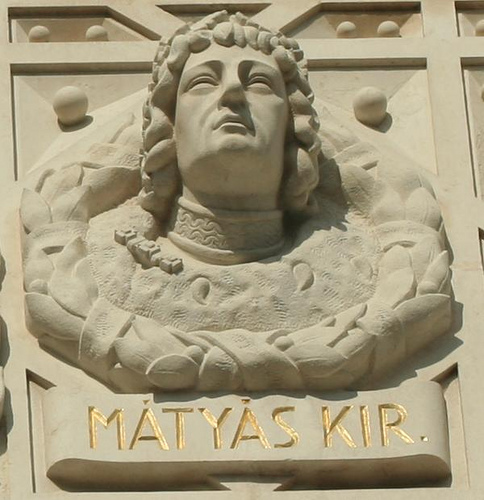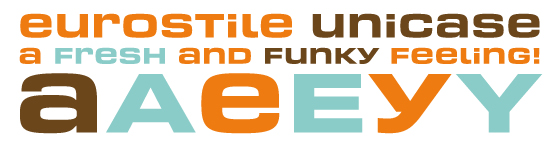
Unicase-Schrift mit Umlauten
ich versuche gerade, eine relativ breit laufende und eher fette unicaseschrift zu entwerfen, und komme mit den Umlauten nicht weiter. Zum Vergleich: etwa so wie die (eurostile unicase)
Ich störe mich total daran, dass die ä-/ö-/ü-Pünktchen die einzigen Elemente sind, die dann aus der so geradlinigen und sauberen gleichen Höhe herausragen.
Was meint ihr, wäre es um der Gleichmäßigkeit Willen in Ordnung, wenn ich statt ä ein æ, statt ö ein œ und statt ü irgendwas ähnliches – ein zusammengezogenes ue – einbaue, oder bricht das die orthografischen Regeln zu sehr und irritiert nur?
Wart mal aufs TypoJournal 4 (kommt in 3 Wochen oder so). Da hat Florian Hardwig in einem Artikel alle Methoden, die Umlaute einzubauen und einzuziehen klassifiziert und mit Beispielfotos versehen. Da kannst du dir einen perfekten Überblick verschaffen. :-)
wenn ich statt ä ein æ, statt ö ein œ
Mhh, nee.
Besser wären OpenType-Varianten. Mal eingezogen, mal nicht.
ich weiss nicht was du mit der schrift vor hast aber es gibt mehr zeichen als ä, ö, ü es gibt auch é, á, ǎ, ñ u. s. w. die lassen sich schwer anders darstellen.
Ja, dass es mehr Umlaut- und Akzentzeichen gibt, weiß ich auch ;) Aber für die geplante Anwendung werden nur äöü gebraucht.
Leider muss die Schrift noch diese Woche fertig (bzw. benutzbar :baeh: ) werden. Ja, dann werd ich es wohl mit verschiedenen OpenType-Varianten versuchen.
Aber ich bin dennoch sehr gespannt auf den Artikel bzw. auf das ganze Journal! :-P
Und wie wäre es, wenn man es ähnlich wie in deinem Beispiel mit der Eurostyle Unicase mit dem kleinen i macht, hier ist ja auch der Punkt in das Rechteck hinein gezogen, und dafür eben der Buchstabe in der Höhe verringert. Beim Ä lassen sich die Umlaut-Punlte ja auch rechts und links neben den eher dreieckigen Buchstaben setzen, beim Ü würde ich die senkrechten Stämme des U einfach teilen, undf beim Ö das O verflachen, und die Umlaut-Punkte eher breit machen, um so wieder das gefüllte Rechteck zu erzeugen.
So ähnlich hatte ich das schon ausprobiert, sah aber wegen der breiten Buchstaben sehr unausgeglichen aus und die Umlautbuchstaben wirkten wie Fremdkörper, die viel mehr ins Auge gefallen sind, als mit Überlängen. Deshalb hab ich es erstmal bei Überlängen belassen…
Grinsekatze, du könntest auch mit Aussparung arbeiten. Hier eine schnelle Skizze:
Das geht natürlich viel, viel schöner, als ich es hier gemacht habe.
Ich musste spontan an das 800-Jahre-Dessau-Logo denken. ;-)
Bei deinem Beispiel habe ich das Problem, dass es sich potenziell um ein Ö und Ü handeln könnte. Wie wäre es stattdessen damit, die Punkte in die Binnenräume/Punzen der Buchstaben zu verbannen? Die Ö-Punkte in die Punze des Ös usw.
Darüber hinaus findest du in der Flickr-Gruppe Fancy Diacritics reichlich Inspiration für Möglichkeiten der Umlautpositionierung.
Z.B. in der Super Grotesk? [PDF-Muster]
Ansonsten lohnt zur Inspiration ein Blick nach Ungarn. Im Ungarischen gibt es viel mehr Diakritika als im Deutschen (ÁÉÍÓÖŐÚÜŰ) und sie kommen auch noch viel häufiger vor als unsere Umlaute. Dazu kommt, dass Auftraggeber von Beschriftungen an Gebäuden anscheinend ein besonderes Faible für Versalsatz haben, der Platz für die vielen Diakritika aber oft nicht ausreicht. Da wird dann gequetscht und herum geschoben, oft mit suboptimalen Ergebnissen …
Aber Gestalter, die ein bisschen weiter denken, setzen oft auf negative space, d.h., sie nehmen den Basisbuchstaben und stanzen in diesen Aussparungen, die an die Diakritika erinnern. (Leider habe ich dafür auf die Schnelle keine Beispiele gefunden, aber man kann es sich sicher vorstellen.)
etwa so?
Im Prinzip ja, obwohl genau diese Lösung mit geschlossenen Konturen extrem selten sein dürfte. I.a.R. wird der Basisbuchstabe einfach angeschnitten. Besonders wirkungsvoll geht das bei den Buchstaben mit Strichakzenten (also ÁÉÍÓŐÚŰ), denen man einfach eine dreieckige Kerbe (oder bei Ő und Ű, zwei) rein haut. Ich habe auch schon Lösungen für das É gesehen, bei denen der obere Querbalken des E am Ende einfach schräg abgeschnitten wurde. Im Kontext funktioniert das wunderbar. Es ist auch möglich, für Á, É, Í, Ó und Ú eine schmale horizontale weiße Linie über den oberen Teil des Basisbuchstabens zu legen. Das sieht dann zwar besonders beim E eher aus wie Ē, was im Ungarischen aber kein Problem ist.